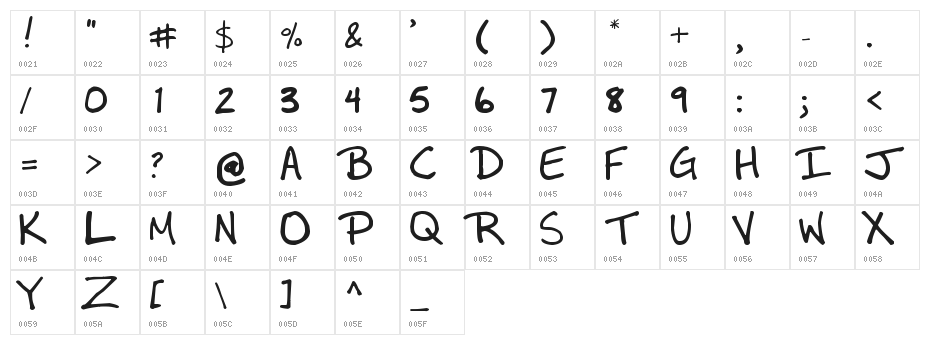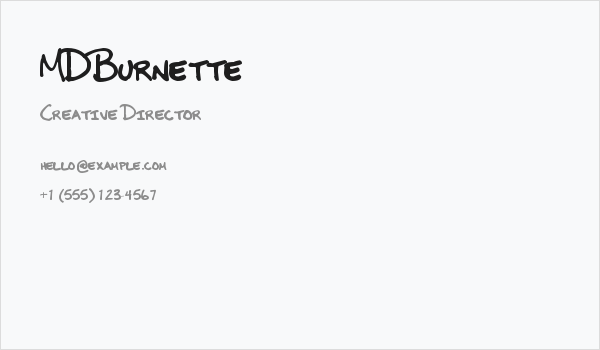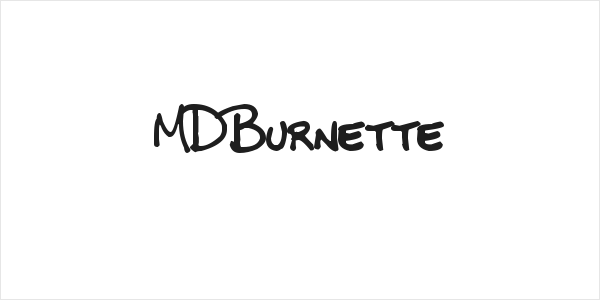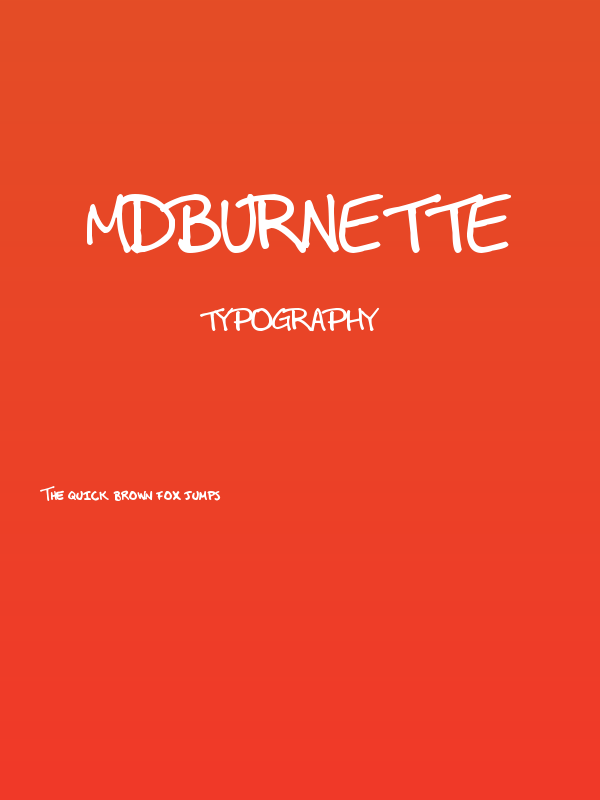
MDBurnette Font
| Stile generale | Casual |
| Progetti proposti | Ideal for greeting cards, children's books, casual branding, and social media graphics. |